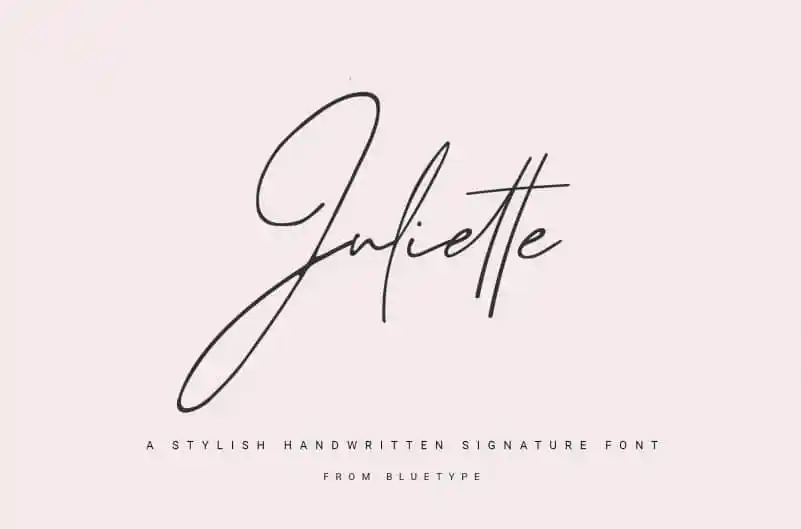
Juliette – Signature Font – Download Grátis
Juliette é uma fonte assinatura que captura a essência natural e autêntica do traço manual. Manufacturada pela Bluetype, esta fonte é perfeita para aqueles buscando um toque de elegância e simplicidade em seus projetos digitais. Com uma gama completa de letras minúsculas e maiúsculas, números e sinais de pontuação, a Juliette oferece também símbolos multilíngues, alternativas de letras minúsculas e uma seleção de ligaduras. Esta font é ideal para aplicações que exigem um toque pessoal ou sofisticado. Combinada com seu charme natural e sua simplicidade pura, a Juliette oferece um estilo único e extremamente estiloso, tornando-se uma escolha inteligente para criações de marca, cartas assinadas, convites de casamento, promessas, embalagens de produto e muito mais. E em cada traço e curva, você encontra a autenticidade que tanto valoriza nas suas criações.